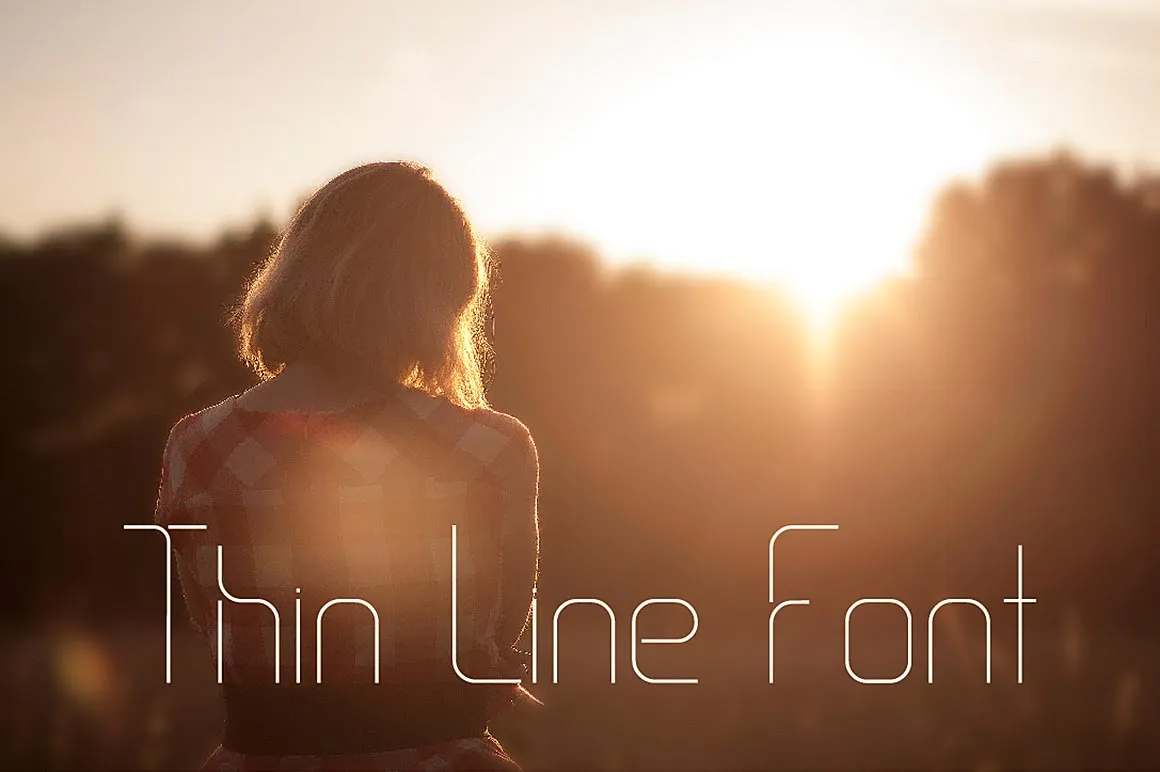
A fonte ‘Thin Line Font’, criada pelo designer Hamilton, oferece uma experiência visual única para os designers digitais brasileiros. Seu estilo minimalista e contemporâneo é perfeito para aplicar um toque clean e moderno nos projetos gráficos. Este display font traz elegância sem excessos, ideal para headlines e elementos chamativos em qualquer projeto de design. A qualidade clara e a simplicidade da ‘Thin Line Font’ garantem que ela seja fácil de ler ao mesmo tempo que oferece um contraste visual atraente. Para designers brasileiros, essa fonte é uma ótima escolha, se você busca incorporar um elemento elegante e atual em seu trabalho sem perder o conforto na leitura. Descarregue-a agora e divirta-se com esse design minimalista incrivelmente sofisticado.